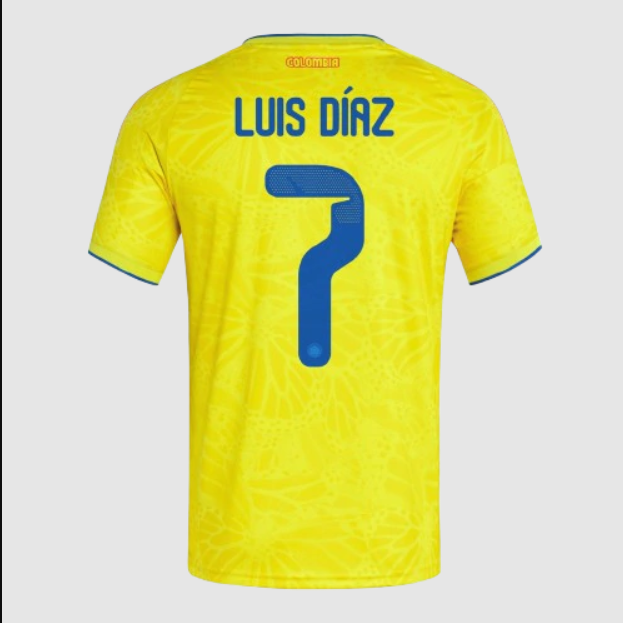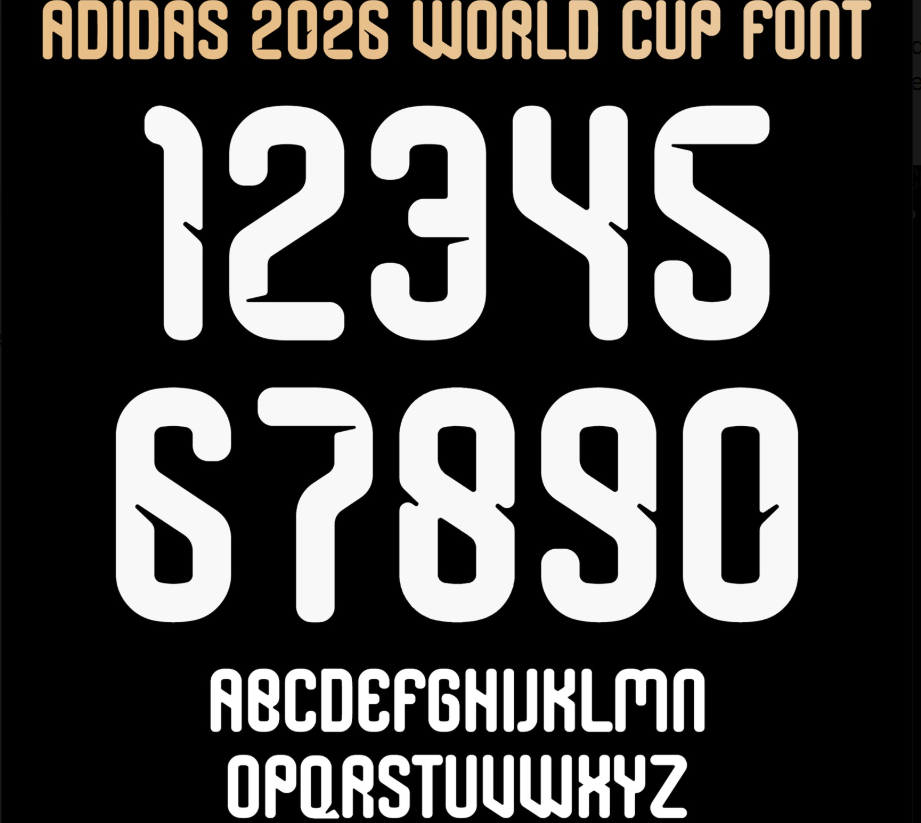
Fonte Colômbia 2026 (Adidas) – Download TTF e Vetor para o Ciclo da Copa
A caminhada rumo à Copa do Mundo de 2026 nos Estados Unidos, México e Canadá já começou, e a Seleção Colombiana entra em campo com um visual renovado. A parceria com a Adidas trouxe para Los Cafeteros um kit que une a vibração das cores tradicionais com um design tipográfico moderno e arrojado.
Estilo Visual e Design
A tipografia desenvolvida pela Adidas para este ciclo da Copa 2026 aposta em uma estética dinâmica. As fontes da marca alemã para as federações nacionais têm buscado inspiração em arquivos retrô, mas com uma execução futurista.
No caso da Colômbia, a fonte apresenta caracteres com espessura média e cortes angulares que transmitem velocidade e movimento. Ela foi desenhada para ser altamente legível tanto nas transmissões em 4K quanto nas arquibancadas, destacando-se perfeitamente sobre o fundo amarelo vibrante da camisa titular. É a peça que falta para deixar a sua personalização com “cara de jogo oficial”.